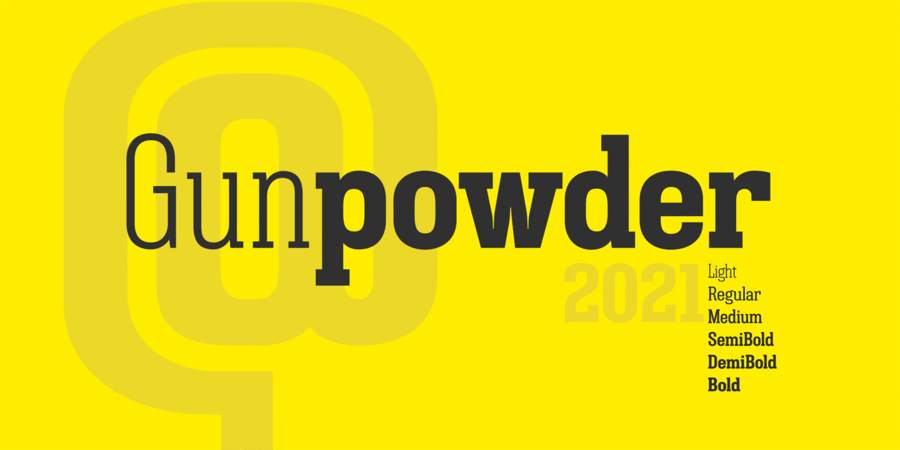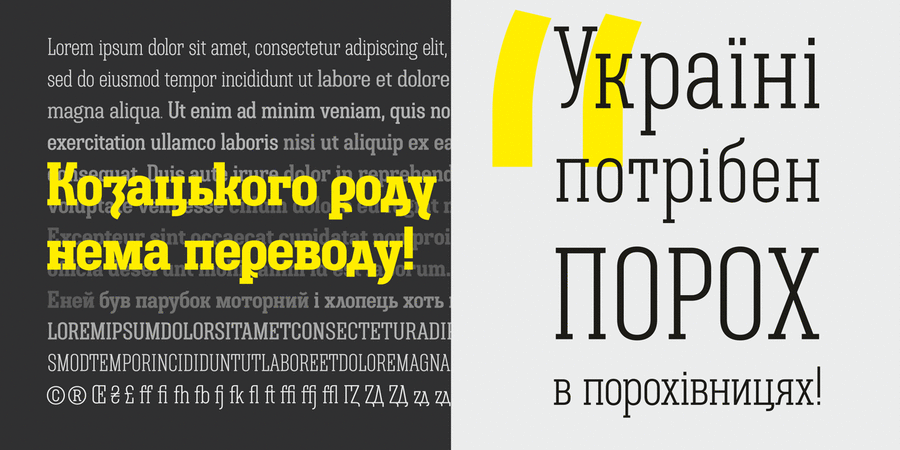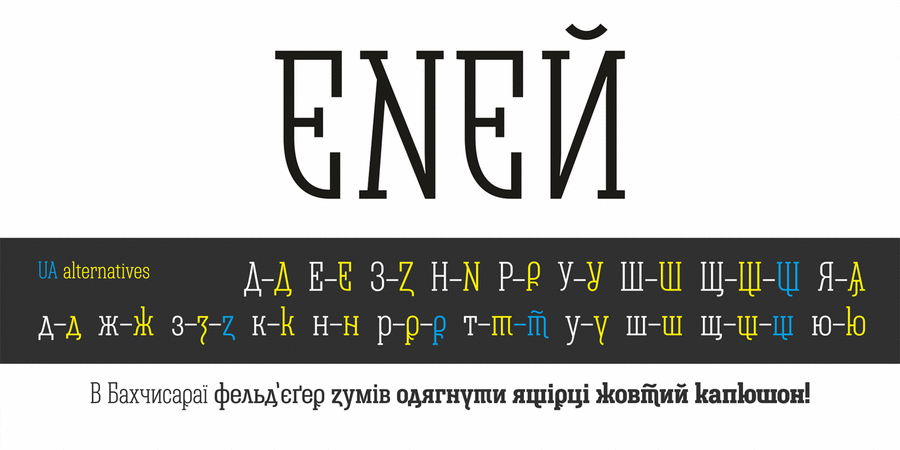
Це вузький геометричний брусковий шрифт зі спокійним характером у 6 накресленнях. Сфера використання — акциденція. Gunpowder підтримує латинку, кирилицю, українську кирилицю в якості альтернативного стилістичного набору, має багато лігатур. Шрифт розробила Тетяна Іваненко в 2021 році.
Особливості сімейства шрифтів Gunpowder ITХіт десятиліття:
Асоціації з сімейством шрифтів Gunpowder ITОсобистість і характер гарнітури:
стрункий, худий, рівний, статичний, високий, серйозний, міський, вузький, технічний, якісний, точний, чіткий, дорослий, стійкий, стабільний, твердий, гучний, впевнений, помітний, амбітний, важливий, мотивуючий, переконливий, міцний, сильний, техногенний, індустріальний, мужній, значний, прямокутний, надійний, суворий, яскравий, активний, крутий, грубий, різкий, робочий, важкий, залізний, сталевий
Місто, хмарочос, дієта, кафе, новини, політика, будівництво, нерухомість, завод, промисловість, влада, техніка, інструмент, будматеріали, верстат, індустрія, енергетика, джинси, ремонт, охорона, захист, блокбастер, Футбол, робочий, Локдаун, нафта, поліція, металургія Гарнітура має ознаки стилів: